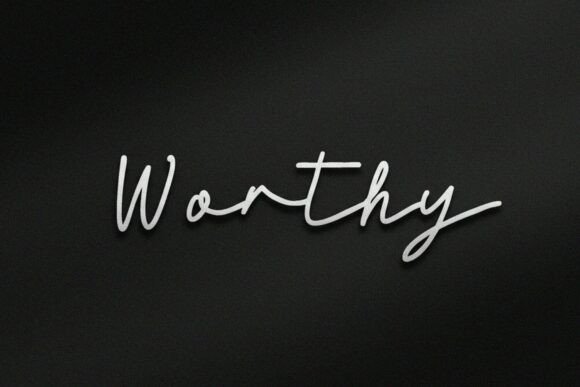
Worthy
適切なデザイン要素を見つけるのは難しい場合がありますが、Worthyは作品を即座に引き立てる優れたコレクションを提供します。
精密に作られたWorthyは、クリーンなベクター、滑らかなタイポグラフィ、そして安心のための商用ライセンスを提供します。
POD(オンデマンド印刷)製品、結婚式の招待状、またはソーシャルメディアのグラフィックを作成している場合でも、Worthyは理想的です。